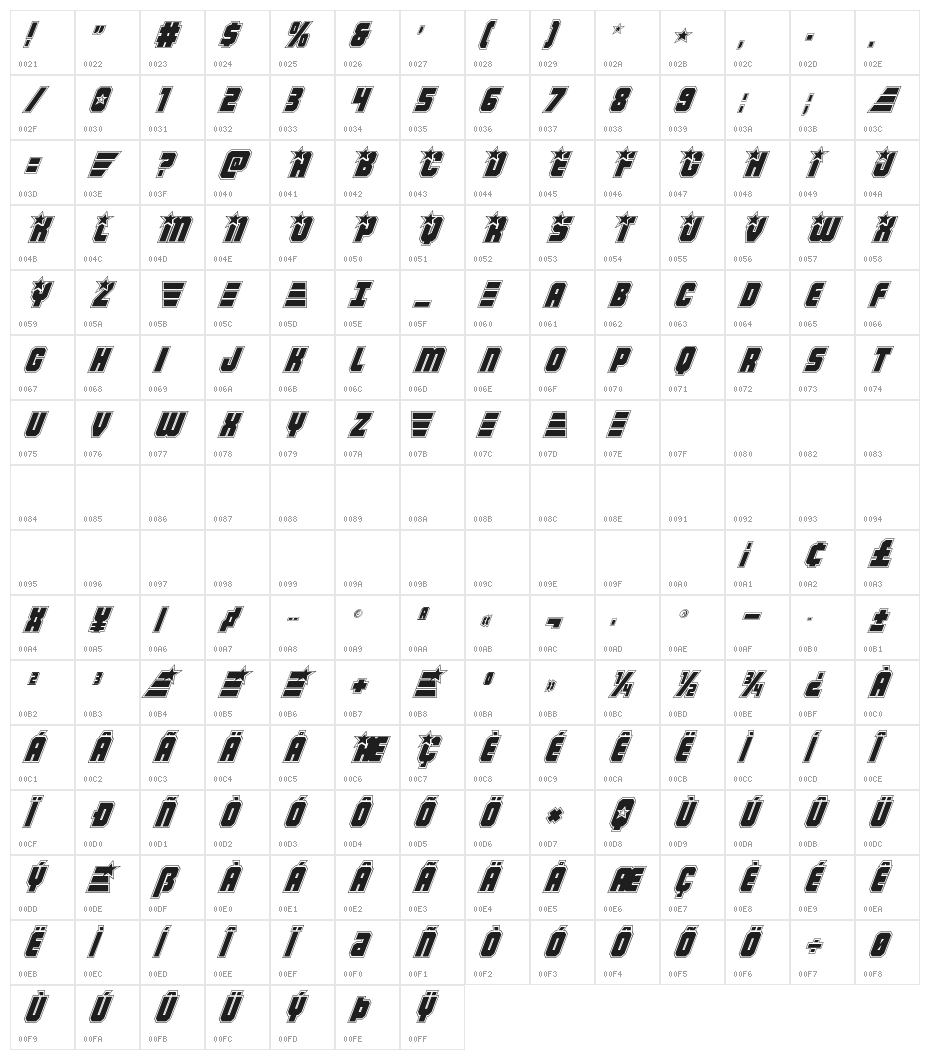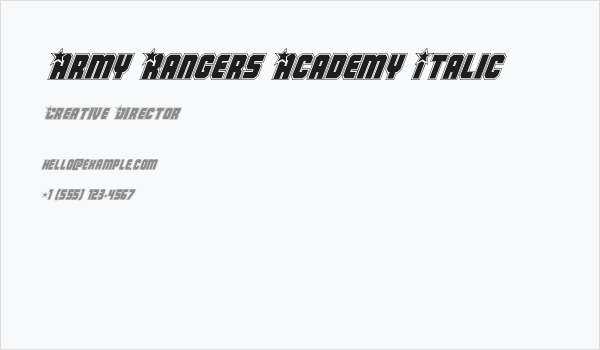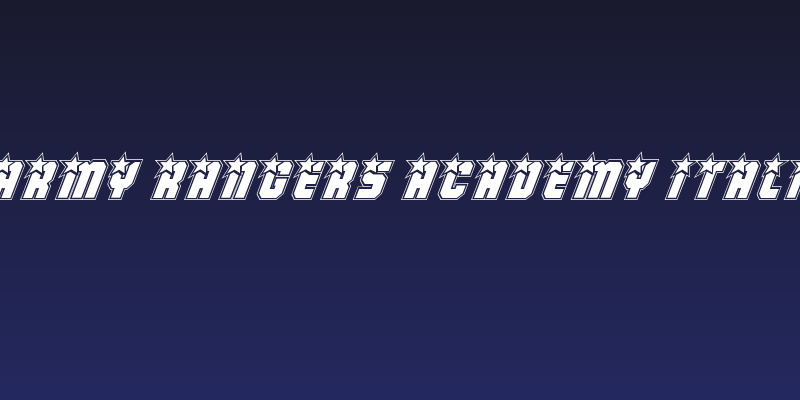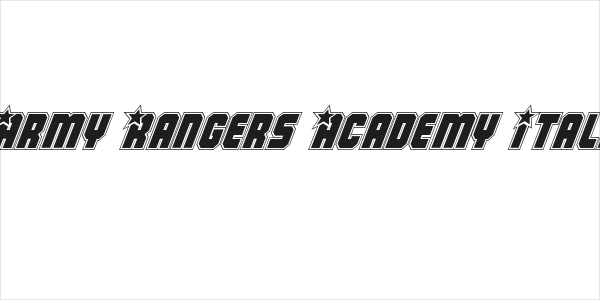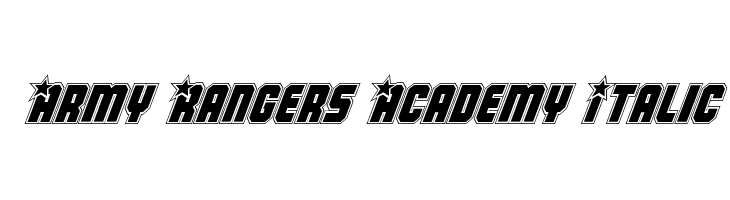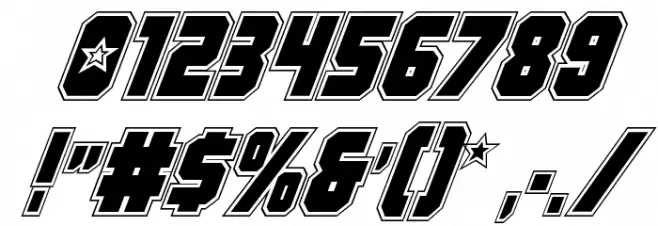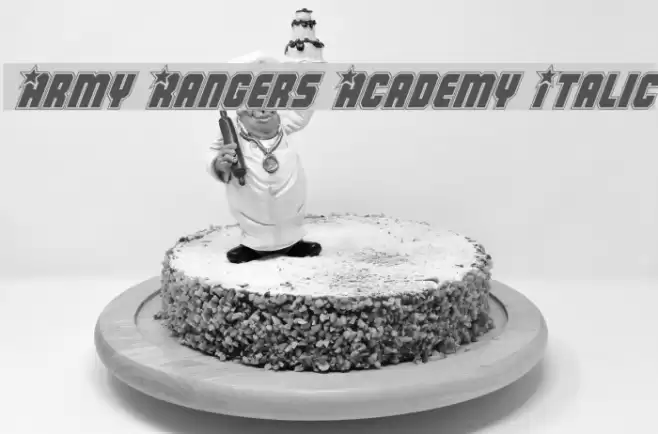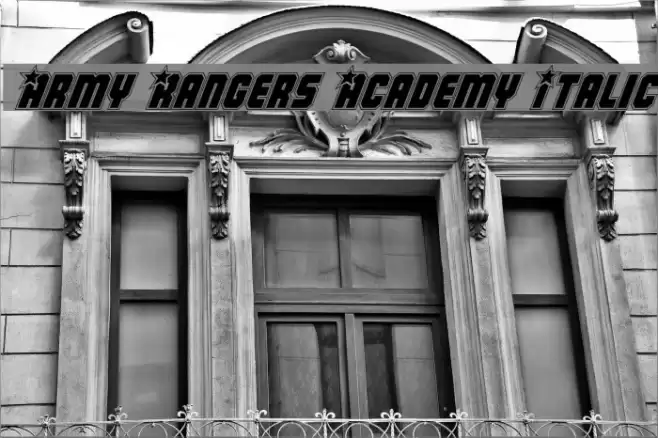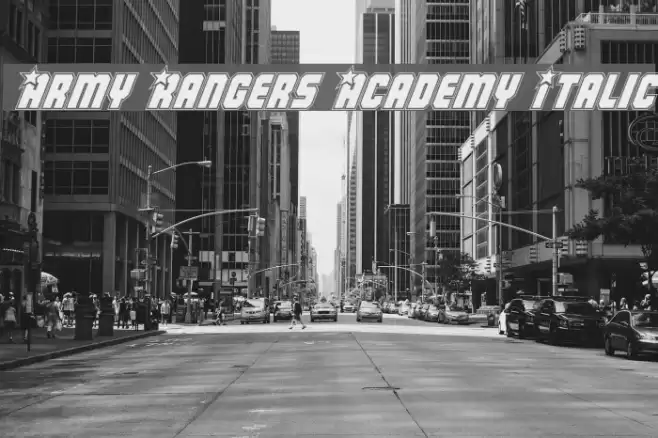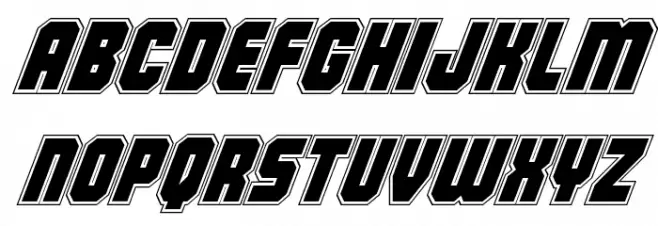
Army Rangers Academy Italic Font
| Progetti proposti | Ideal for military-themed designs, sports team logos, action movie posters, or any project needing a bold, impactful typeface. |